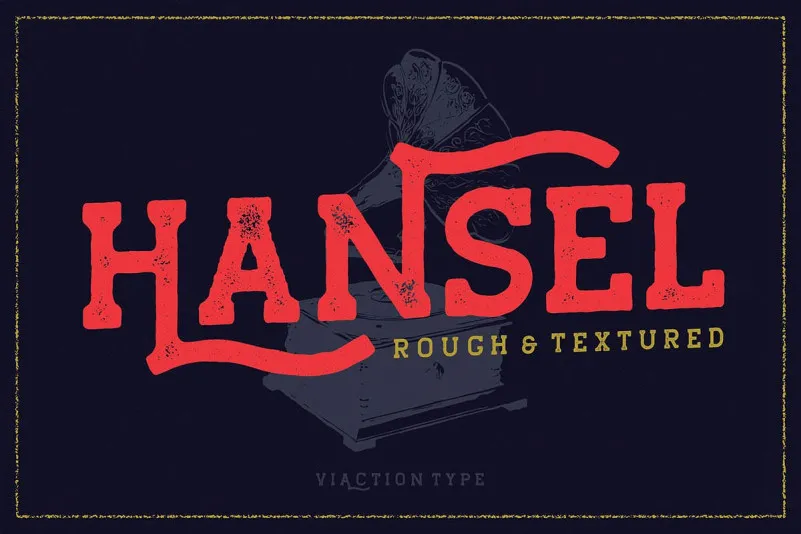
Hansel Slab Serif Font – Download Grátis
A Hansel Slab Serif é uma fonte ideal para designers amantes de letras que buscam um estilo vintage em suas criações. Com seu toque moderno e rusticamente elaborado, essa fonte é perfeita para criar logomarcas de produtos, convites de casamento, marcas de roupas e design vintage. Além disso, sua extensão multilíngue e alternativas estilísticas completam a experiência de usar Hansel. Hansel se destaca não apenas por ser uma fonte slab serif com duas opções de estilo (rough & textured), mas também pelo seu potencial em várias aplicações. Essa fonte é perfeita para criações que exigem um tom vintage, seja ela em rótulos ou posters, embalagens de produtos ou design de logomarcas – tudo isso com uma fidelidade única e autêntica ao estilo do século XIX. Essa fonte, criada pelo designer 24Design, é uma excelente escolha para qualquer projeto que deseja incorporar um toque vintage sem perder a modernidade. Combinada com outros elementos de design, pode transformar sua arte em algo único e memorável.